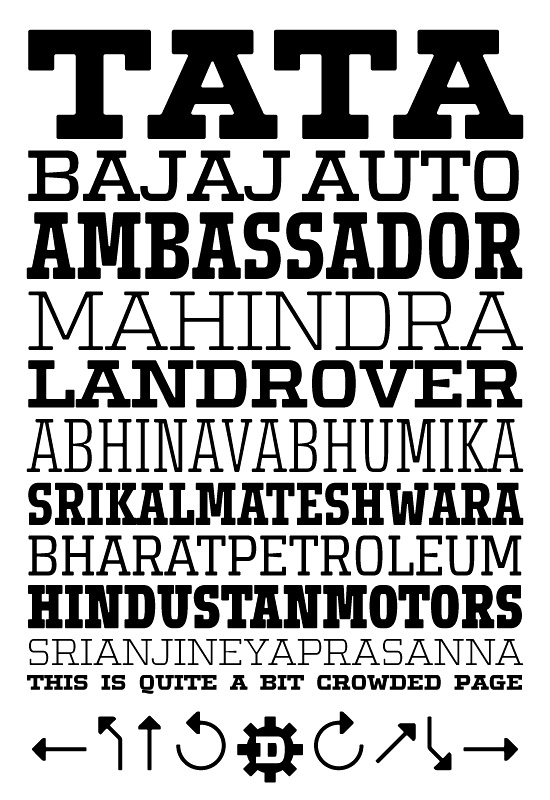
Defender (Stormtype)
Das J scheint einfach zu weit nach links gerutscht sein. Es klebt auf dem A links daneben, und lässt rechts zu viel Platz.
Ich weiß auch wie solche Sachen entstehen ... Einmal mit der Maus versehentlich durchs Metrik-Fenster in Fontlab geräubert, und schon hängt das getroffene Zeichen *irgendwo*. Wenns dann nicht gleich auffällt, wie beim "J"...